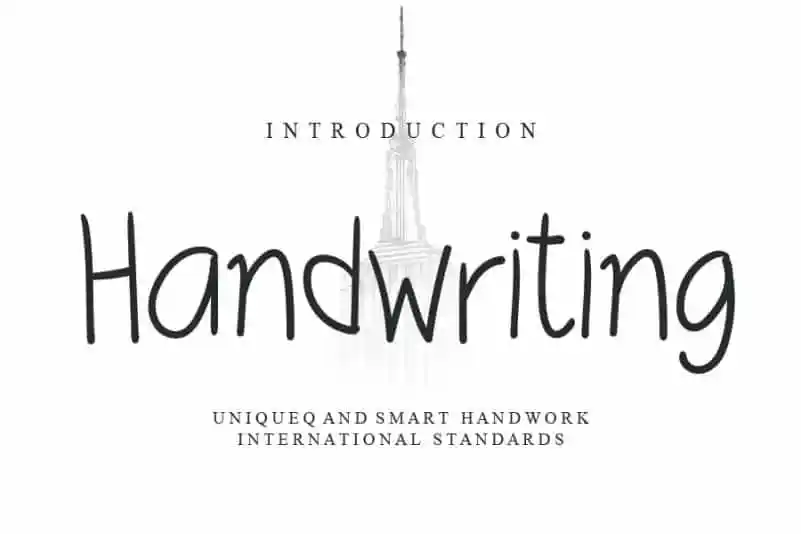
Handwriting Script Font – Download Grátis
A fonte ‘Handwriting Script Font’ é uma escolha perfeita para aqueles que buscam uma combinação única de charme e elegância no design. Com seu estilo clássico, essa fonte mantém um ar descontraído que torna-a ideal para projetos criativos. Ideal para criar designs únicos e destacados, a ‘Handwriting Script Font’ é perfeita para designers amantes da arte que buscam uma linguagem pessoal em seus trabalhos. Com seu design cuidadosamente construído para o público final, ela oferece um toque de personalidade que enriquece qualquer projeto. Seja para rótulos, logos ou letras do texto – a ‘Handwriting Script Font’ torna-se sua amiga de confiança em uma variedade de projetos. Neste contexto brasileiro vibrante e natural, essa fonte se adapta perfeitamente, permitindo que você transmita seu estilo pessoal e singular de maneira autêntica. Que tal explorar a riqueza da nossa cultura ao aplicar esta fonte elegante em seus próximos projetos?